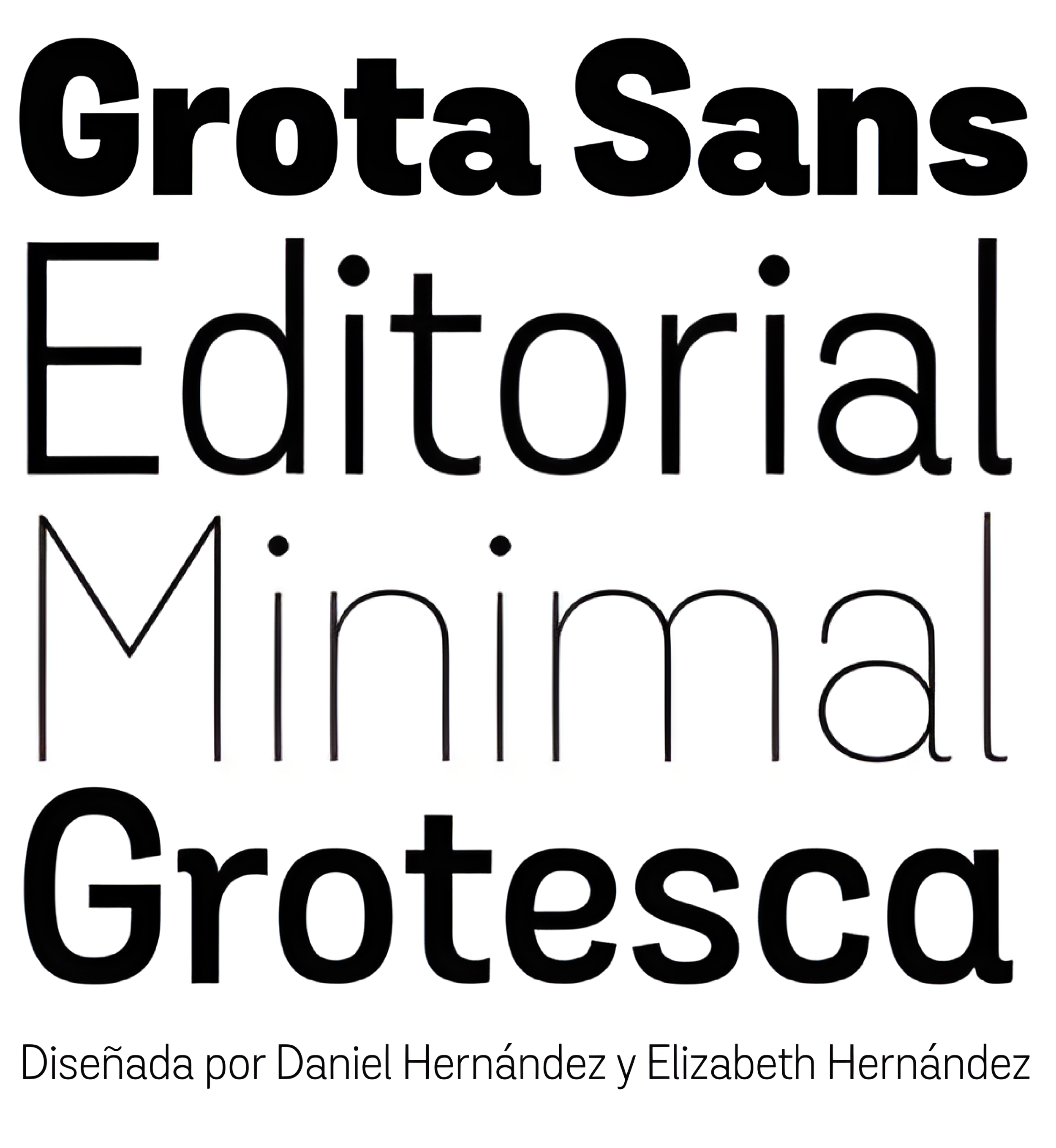
Grota Sans
| Año | 2014 |
| Créditos | Daniel Hermández, Elizabeth Hernández |
| Descripción | Grota vuelve en sus nuevas versiones Sans y Rounded. La familia completa consta de 40 fuentes, 10 pesos diferentes, cursivas y una versión alt. Grota Sans Rounded, diseñada por Eli Hernández y Daniel Hernández, es una fuente grotesca con espíritu latino. Esta fuente acompaña a Grota Sans y Grota Unicase. Es ideal para logotipos, marcas, libros, titulares, etc. |
| Familia(s) | Grota Sans |
| Estilos | 40 |
| Set | Especializado |
| Reconocimientos | Bienal de Tipografía Latinoamericana. Tipos Latinos 2016 |